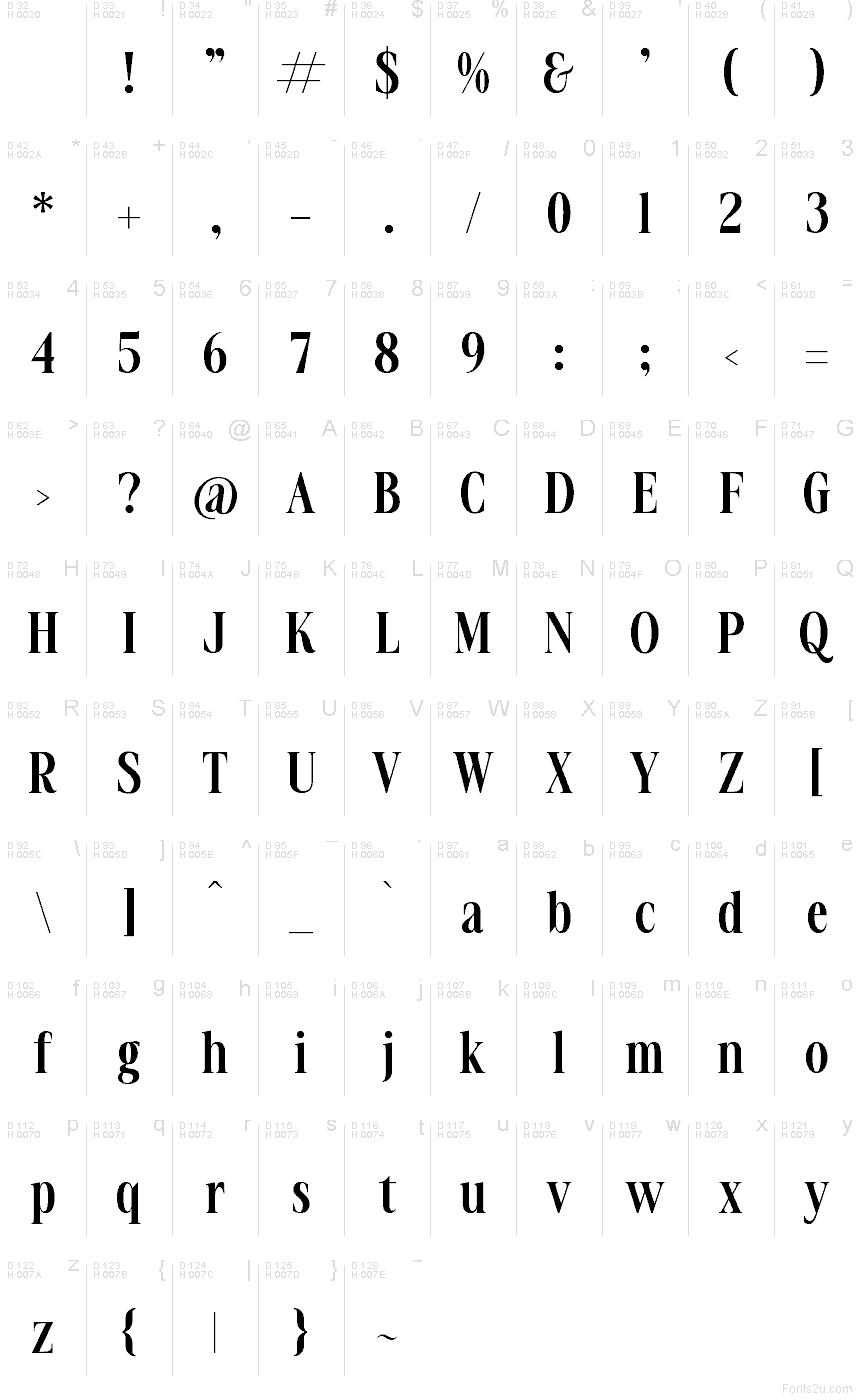
Voilstar od TimelessType.co je bezplatné serifové písmo s vysokým kontrastem a výrazným, módním a redakčním charakterem. Spojení ultra tenkých spojů s vysokými, elegantními křivkami dává písmu vytříbený rytmus, který se hodí spíše k titulním stranám časopisů a luxusním značkám než ke klasické knižní sazbě.
Díky tomu se přirozeně hodí na kosmetické obaly, loga butiků, nadpisy na obálkách, pozvánky a titulní karty, kde trocha dramatičnosti udělá hodně. Jako bezplatný font funguje Voilstar nejlépe v krátkých nadpisech, zejména pokud hledáte štíhlé, vzdušné znaky s ostrým, glamour nádechem, spíše než něco hřejivého či rustikálního.